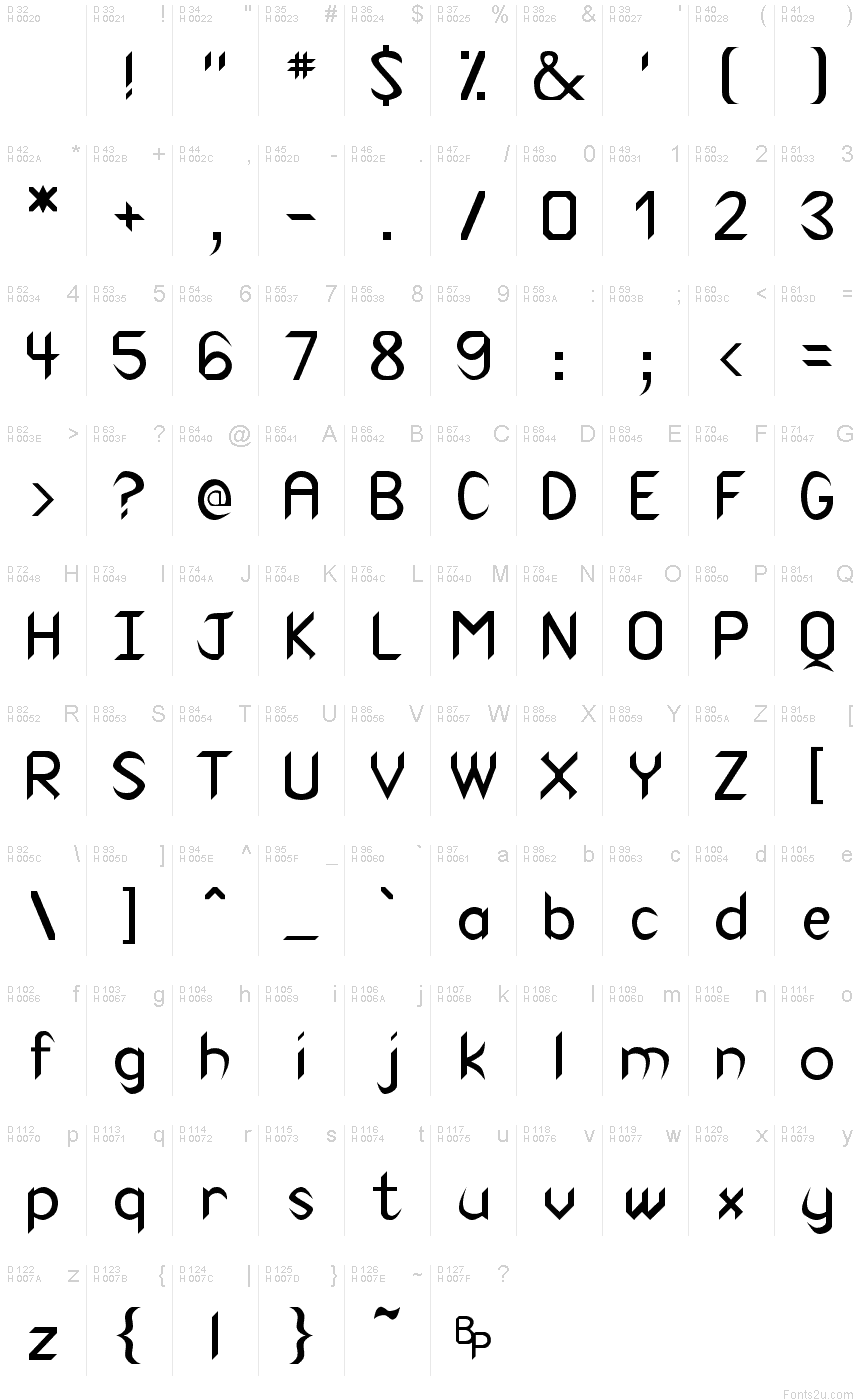
Krój Canuth wnosi ostrą, pędzlową energię dzięki zwężającym się pociągnięciom i rzeźbiarskim krzywiznom, nadając każdej literze dynamiki bez przechodzenia w pełną kursywę. Odważne kształty i kanciaste cięcia sprawiają wrażenie nowoczesnych i lekko mistycznych, dzięki czemu ten darmowy font natychmiast wyróżnia się w każdym projekcie.
Dzięki dramatycznemu rytmowi i charakterystycznym kształtom liter, Canuth świetnie sprawdza się na okładkach książek, w tytułach horrorów czy fantasy, logotypach, plakatach, opakowaniach oraz śmiałych projektach brandingowych. Ten darmowy font najlepiej wygląda w większych rozmiarach, gdzie jego ostre detale mogą w pełni wybrzmieć, a w tekstach towarzyszących dobrze komponuje się z czystym krojem bezszeryfowym.
Canuth